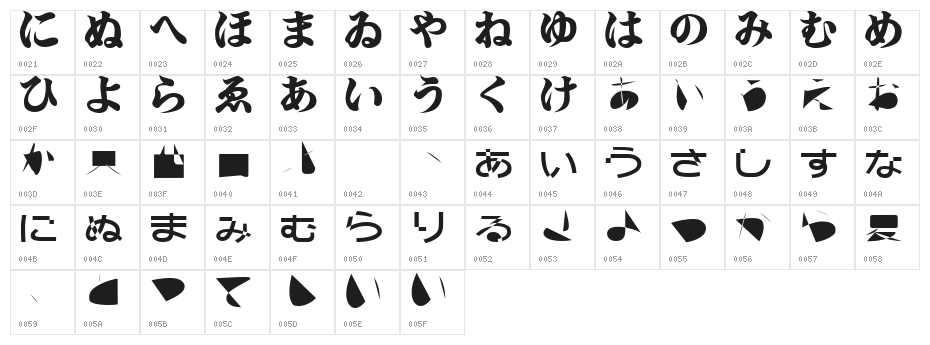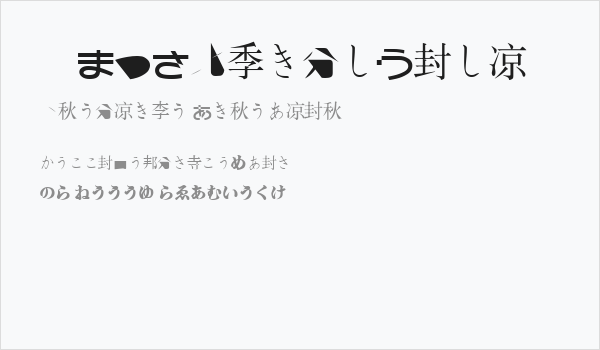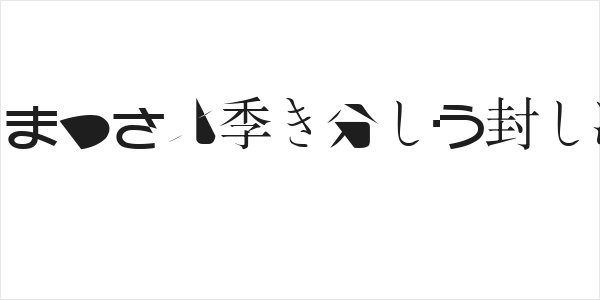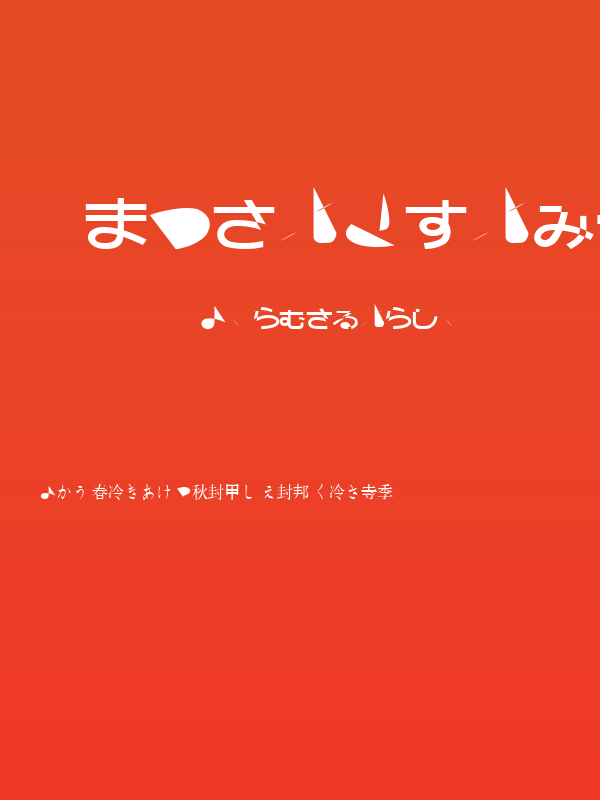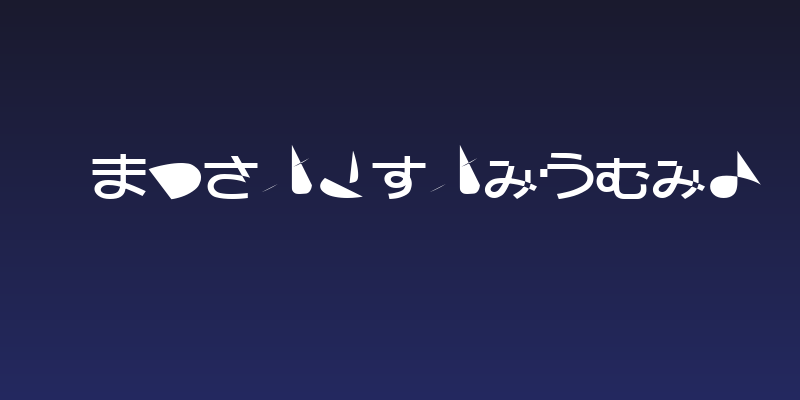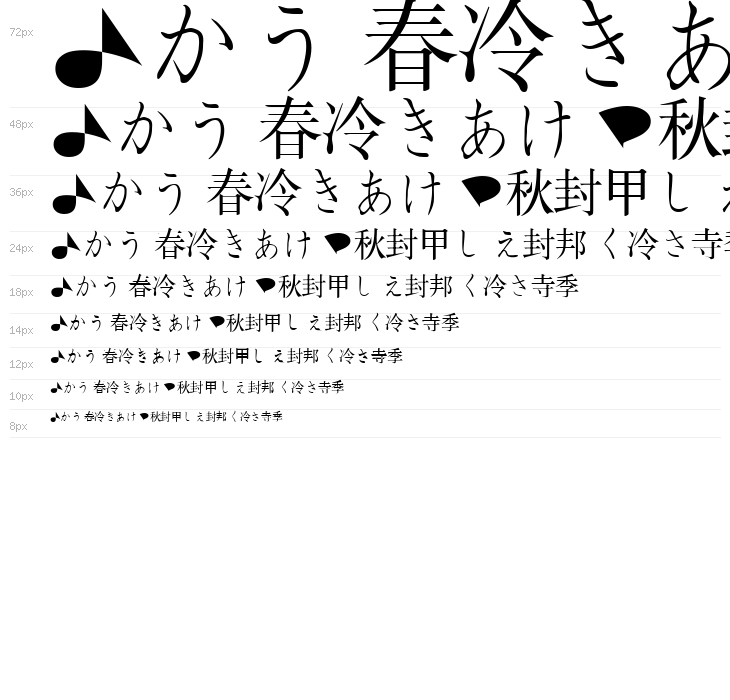
BMUGAsianFont Font
Esta fonte inclui 123 caracteres. Clique em qualquer caractere para ver os detalhes.
| Estilo geral | Modern with traditional influences |
| Caso de uso | Headlines, Posters, Branding, Educational materials |
| Projetos propostos | Japanese branding, editorial headlines, posters, cultural event materials, educational resources. |